WhatsApp Schriftart Status: So hebst du dich ab
Der WhatsApp Status ist längst mehr als nur ein kurzer Text – er ist ein Ausdruck deiner Persönlichkeit. Während viele Nutzer die Standardeinstellungen verwenden, suchen kreative Köpfe ständig nach Wegen, um aus der Masse herauszustechen. Wenn du dich fragst, wie du eine besondere whatsapp schriftart status nutzen kannst, um die Aufmerksamkeit deiner Kontakte auf dich zu ziehen, bist du hier genau richtig. In diesem Artikel zeigen wir dir, wie du deinen Status mit einfachen Mitteln optisch aufwertest und welche Möglichkeiten dir die App sowie externe Tools bieten.
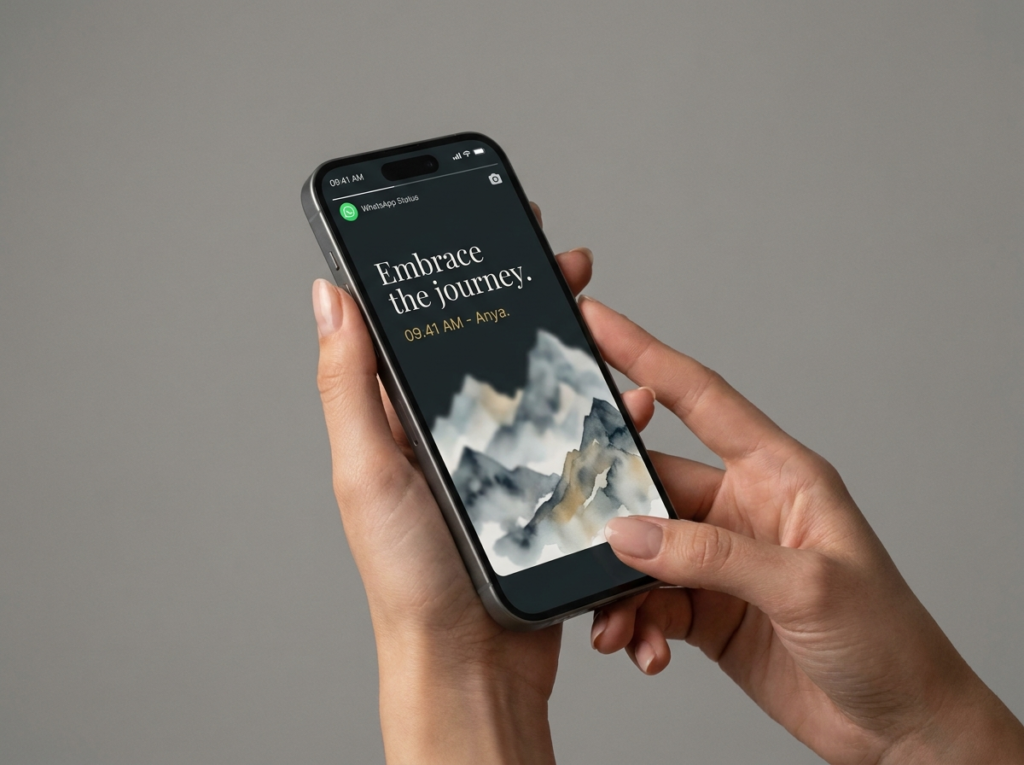
Warum die Wahl der richtigen WhatsApp Schriftart Status wichtig ist
In einer Welt, in der wir täglich mit hunderten Updates überflutet werden, zählt der erste Eindruck. Ein Status, der sich durch eine ästhetische Typografie oder ein besonderes Layout abhebt, bleibt eher im Gedächtnis als ein Standard-Text auf grauem Hintergrund. Die Wahl der Schrift art vermittelt sofort einen Vibe – sei es verspielt, minimalistisch oder professionell.
Die nativen Möglichkeiten in WhatsApp nutzen
Bevor man zu komplizierten Lösungen greift, lohnt sich ein Blick auf das, was WhatsApp bereits von Haus aus anbietet. Viele Nutzer übersehen die versteckten Funktionen, mit denen sich der Text bereits im Editor anpassen lässt.
- Schriftarten-Auswahl: Nutze das “T”-Symbol im Editor, um durch die integrierten Stile zu blättern.
- Farben und Hintergründe: Nutze starke Kontraste, um deine Botschaft hervorzuheben.
Die Psychologie hinter der Typografie
Wusstest du, dass die Art und Weise, wie wir Buchstaben gestalten, eine unbewusste emotionale Reaktion hervorruft? Eine handschriftlich wirkende Schrift vermittelt Nähe und Authentizität, während klare serifenlose Schriften Modernität und Sachlichkeit ausstrahlen. Wenn du ein tiefgründiges Zitat postest, wähle eher eine Serifenschrift für eine zeitlose, seriöse Wirkung.
Strategische Planung: Wann posten?
Nicht nur die Optik entscheidet, sondern auch der Zeitpunkt. Wenn du willst, dass dein Status gelesen wird, nutze Stoßzeiten. Viele Menschen checken ihre WhatsApp-Status-Updates kurz vor der Mittagspause oder am frühen Abend nach Feierabend. Eine visuell ansprechende whatsapp schriftart status hilft dir dabei, in dieser schnellen Phase der Aufmerksamkeit “gestoppt” zu werden.
Kreative Ideen für deine Status-Updates
Wenn dir die Inspiration fehlt, hier sind drei Formate, die mit der richtigen Schriftart besonders gut funktionieren:
- Motivation des Tages: Kurze, knackige Zitate in einer eleganten Serifenschrift.
- Umfragen & Fragen: Nutze ein simples Hintergrundbild und stelle eine offene Frage – das erhöht die Interaktion enorm.
- Behind-the-Scenes: Zeige einen Schnappschuss aus deinem Alltag und nutze die Schreibmaschinenschrift für einen dokumentarischen Look.
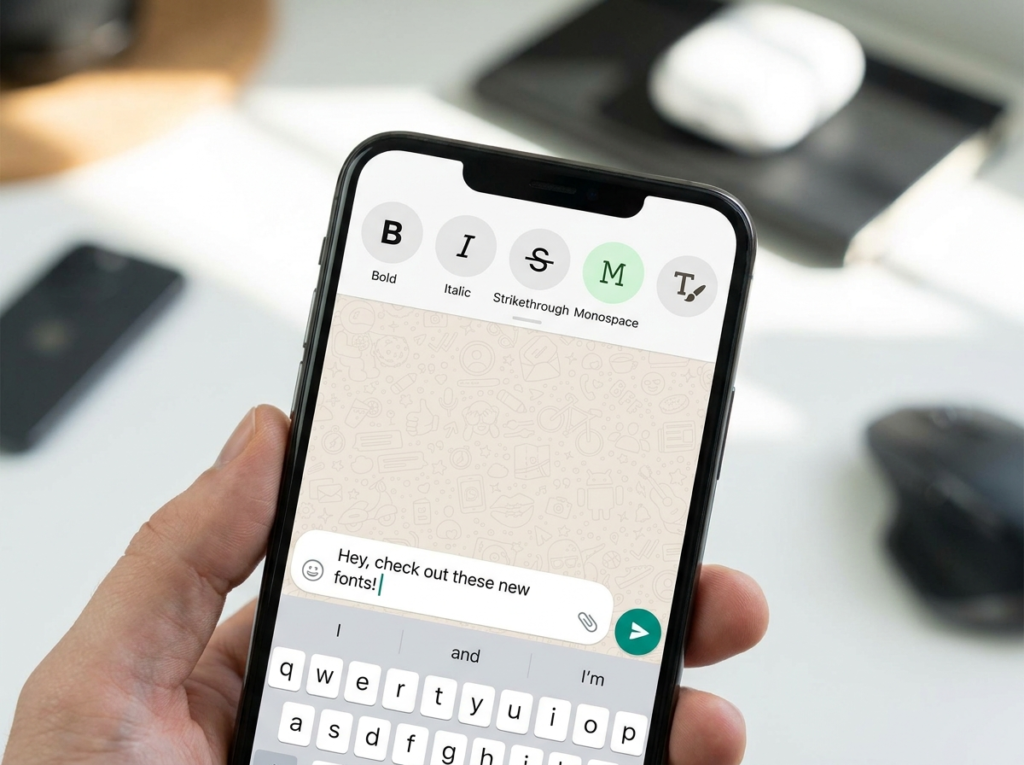
Häufige Fehler, die du vermeiden solltest
Es gibt einige Fallstricke, die deinen Status unprofessionell wirken lassen können:
- Überladung: Zu viele Schriftstile wirken unruhig. Bleib bei maximal zwei Stilen pro Status.
- Technik-Ignoranz: Manche Unicode-Schriften werden auf älteren Geräten als Fragezeichen angezeigt. Überprüfe dein Ergebnis immer kurz auf Kompatibilität.
- Zu viel Text: Wenn du eine lange Geschichte zu erzählen hast, nutze lieber eine Serie von Status-Updates statt alles in einen einzigen Screen zu quetschen.
Häufige Fragen (FAQ)
Warum sieht mein Status bei Freunden anders aus?
Da verschiedene Betriebssysteme (iOS vs. Android) eigene Rendering-Engines haben, können Emojis und spezielle Unicode-Zeichen leicht variieren.
Pro-Tipp für deinen Status:
Nutze Emojis, aber dosiert. Sie sind keine Schriftart, aber sie ergänzen den Text hervorragend, wenn der Stil zur gewählten Typografie harmoniert.
Fazit: Dein Status, deine Identität
Die Gestaltung deines Status ist eine einfache Art, den digitalen Alltag etwas bunter zu gestalten. Mit der richtigen Kombination aus Bordmitteln und kreativen Ergänzungen wird die whatsapp schriftart status zu deinem persönlichen Markenzeichen. Bleibe authentisch und habe Spaß beim Gestalten!